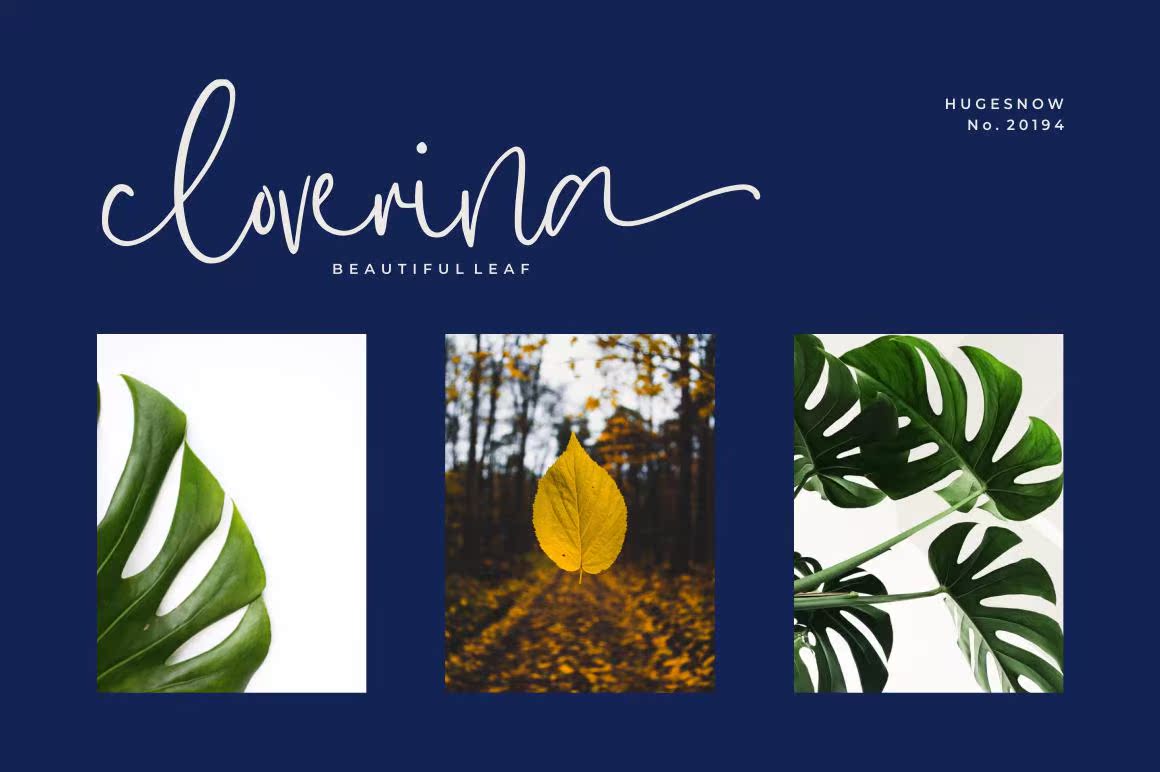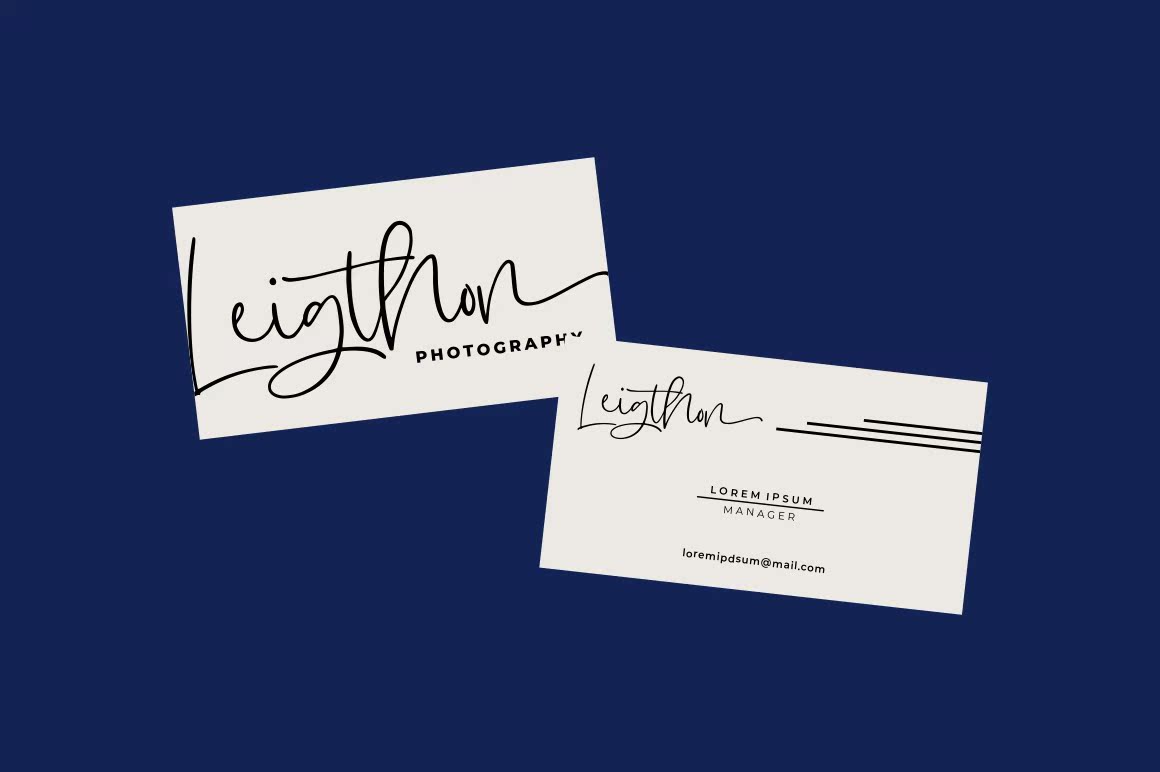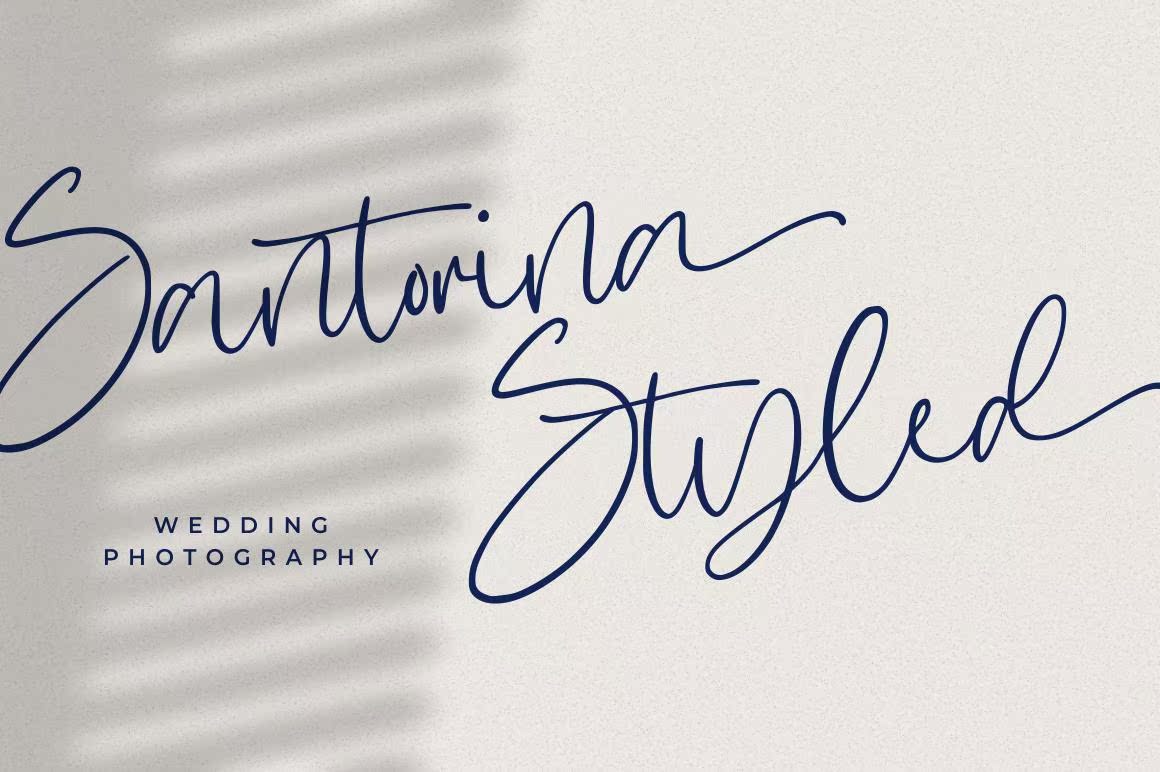
Hugesnow–自然与现代签名和书写字体。我最擅长于徽标、邀请函、文具、婚礼设计、社交媒体、广告、产品包装、产品设计、标签、摄影、水印、特殊物品等。此字体包括:Hugesnow otf TTF WOFF、连字、,还有多种语言支持。Hugesnow–自然与现代签名和书写字体。我非常适合于徽标、邀请、文具、婚礼设计、社交媒体、广告、产品包装、产品设计、标签、摄影、水印、特殊物品或任何东西。此字体包括:Hugesnow TTF WOFF、连字和多种语言支持。